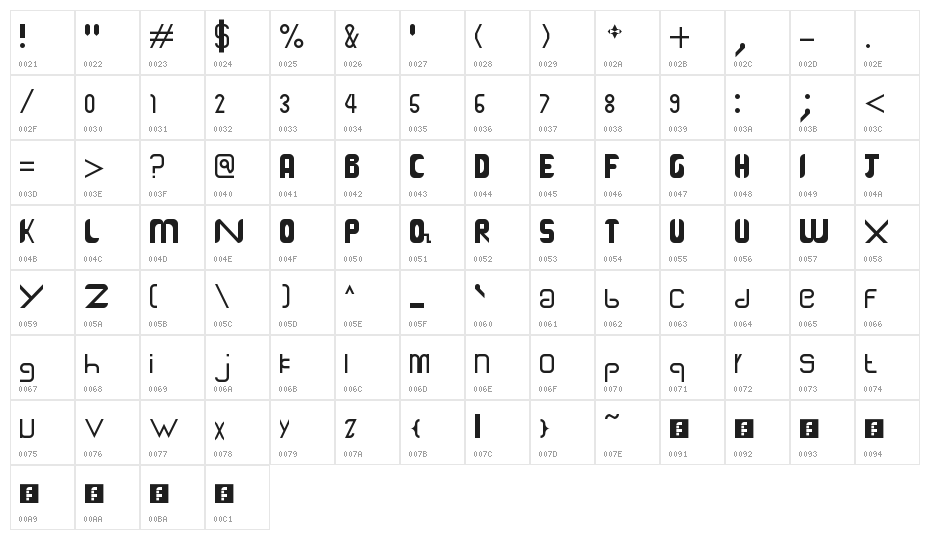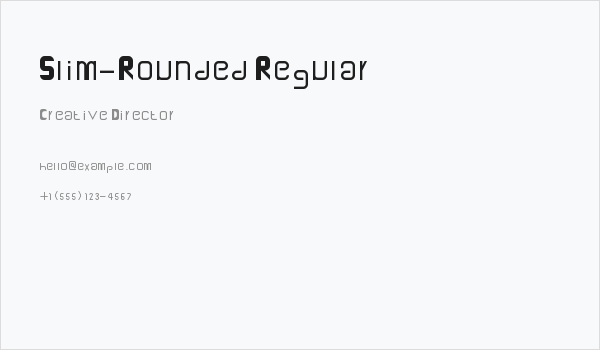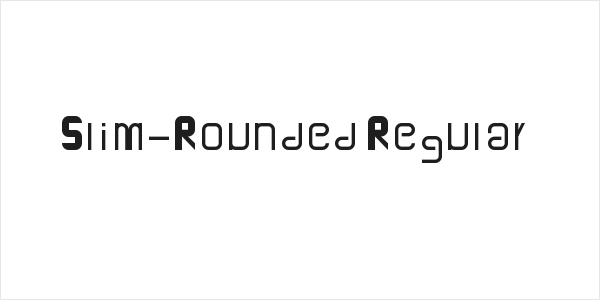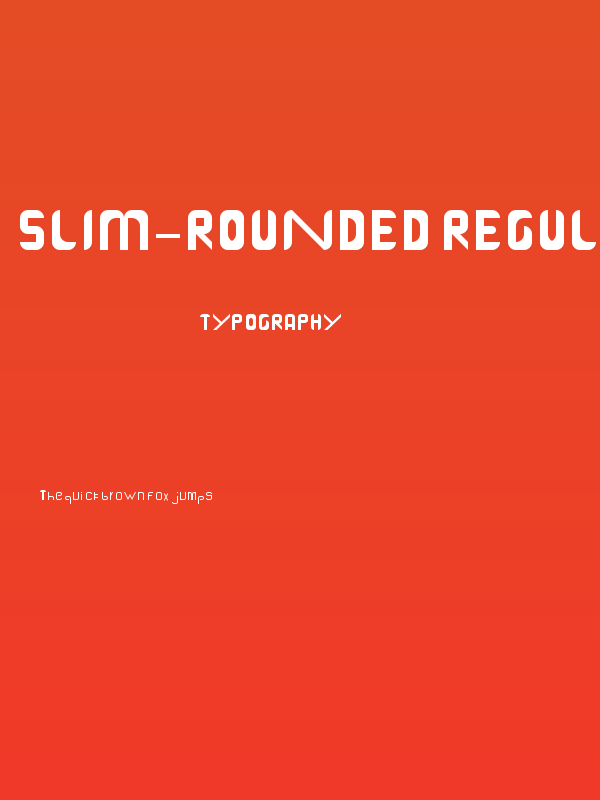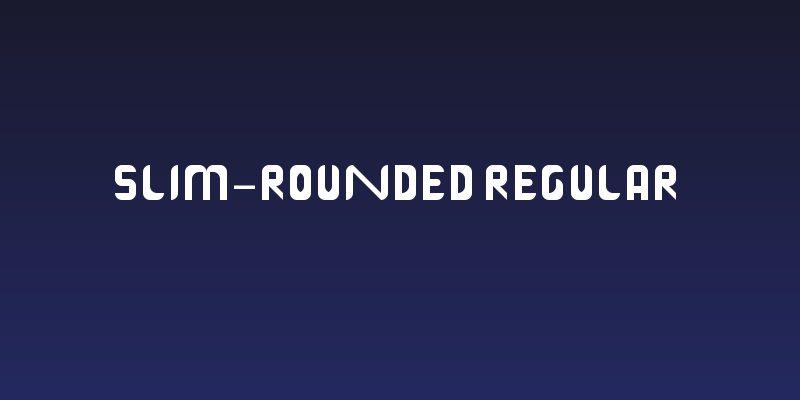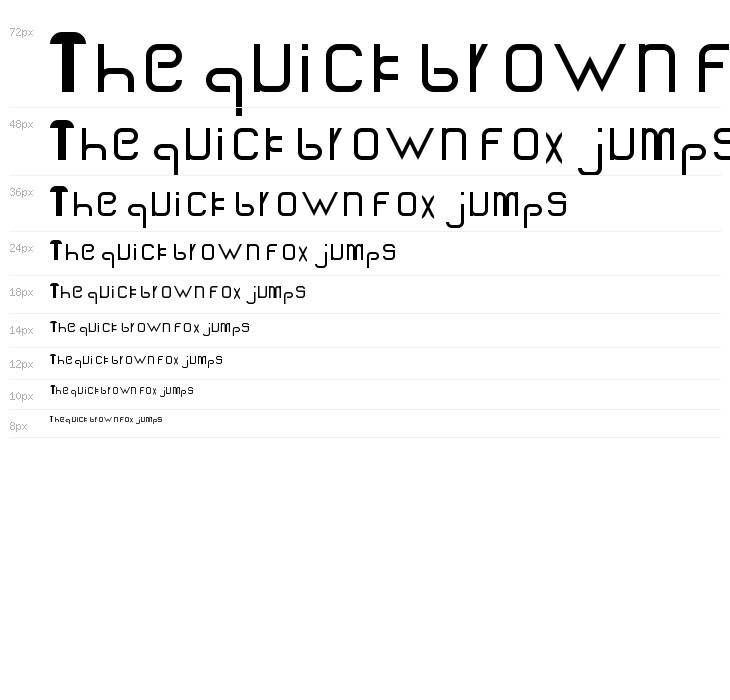
Slim-Rounded Regular Font
| Progetti proposti | Ideal for branding, web design, product packaging, and digital media where a modern and friendly look is desired. |